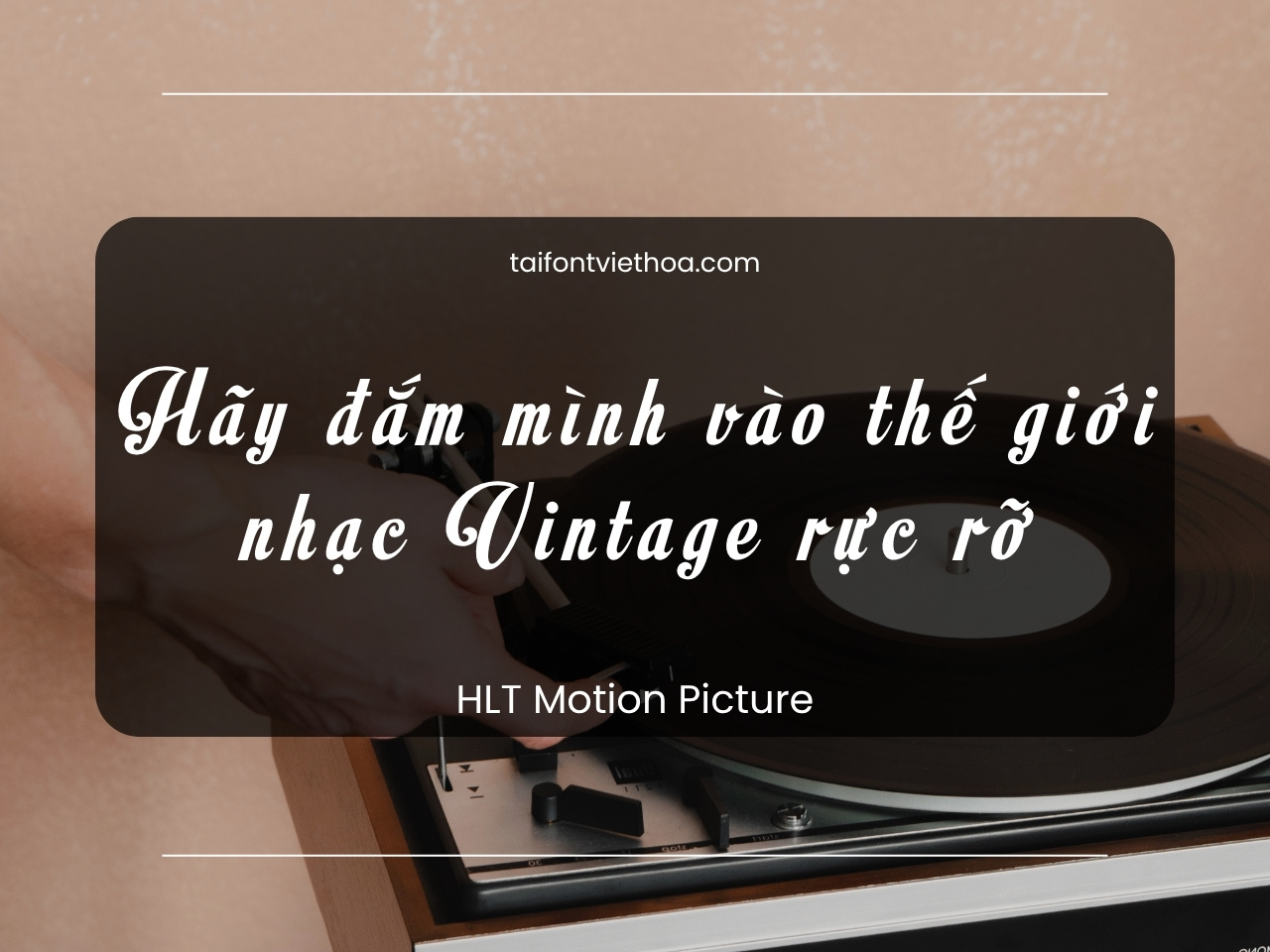
Font việt hóa HLT Motion Picture
Giới thiệu về font Motion Picture – Nét cổ điển Hollywood trong từng nét chữ
HLT Motion Picture là phiên bản Việt hóa từ font gốc “Motion Picture” – một kiểu chữ mang đậm hơi thở Hollywood cổ điển, được thiết kế bởi Emil Bertell (Fenotype). Lấy cảm hứng từ các tiêu đề phim Mỹ những năm 1940–1950, Motion Picture mang lại cảm giác sang trọng, cổ kính và đầy nghệ thuật. Font gốc được phát hành rộng rãi trên các nền tảng font quốc tế và hỗ trợ hơn 70 ngôn ngữ khác nhau, phù hợp với các thiết kế quốc tế đa dạng về ngôn ngữ.
Phiên bản Việt hóa do HLT Fonts thực hiện đã tối ưu đầy đủ hệ thống dấu tiếng Việt, đồng thời giữ nguyên thần thái retro cổ điển đặc trưng. Từng nét uốn lượn, cong mềm của font đều được căn chỉnh chính xác để phù hợp với hệ Unicode tiếng Việt. Font Motion Picture đã được taifontviethoa.com chọn lọc, kiểm nghiệm kỹ lưỡng và giới thiệu lại với cộng đồng thiết kế như một giải pháp sáng tạo cho những dự án đòi hỏi tính hoài niệm và nghệ thuật cao.
Đặc điểm thiết kế và ứng dụng thực tiễn của HLT Motion Picture
HLT Motion Picture có cấu trúc chữ Script dạng uốn lượn (calligraphic), mang dáng dấp của chữ viết tay bằng bút máy. Đường nét thanh mảnh, kéo dài và bo tròn gợi lên hình ảnh poster phim cổ điển hay bìa sách lãng mạn thập niên trước. Font có độ tương phản nhẹ, độ nghiêng mềm mại và một loạt các ligatures giúp văn bản trở nên tự nhiên và liền mạch hơn.
Font rất thích hợp sử dụng trong các thiết kế logo, tiêu đề phim, poster nghệ thuật, bao bì sản phẩm thủ công cao cấp, và đặc biệt là các thiết kế mang phong cách retro, vintage hoặc điện ảnh. Ngoài ra, font còn phù hợp với ngành thiết kế thời trang, quảng bá sự kiện, wedding planner, và các sản phẩm truyền thông đòi hỏi tính biểu cảm cao.